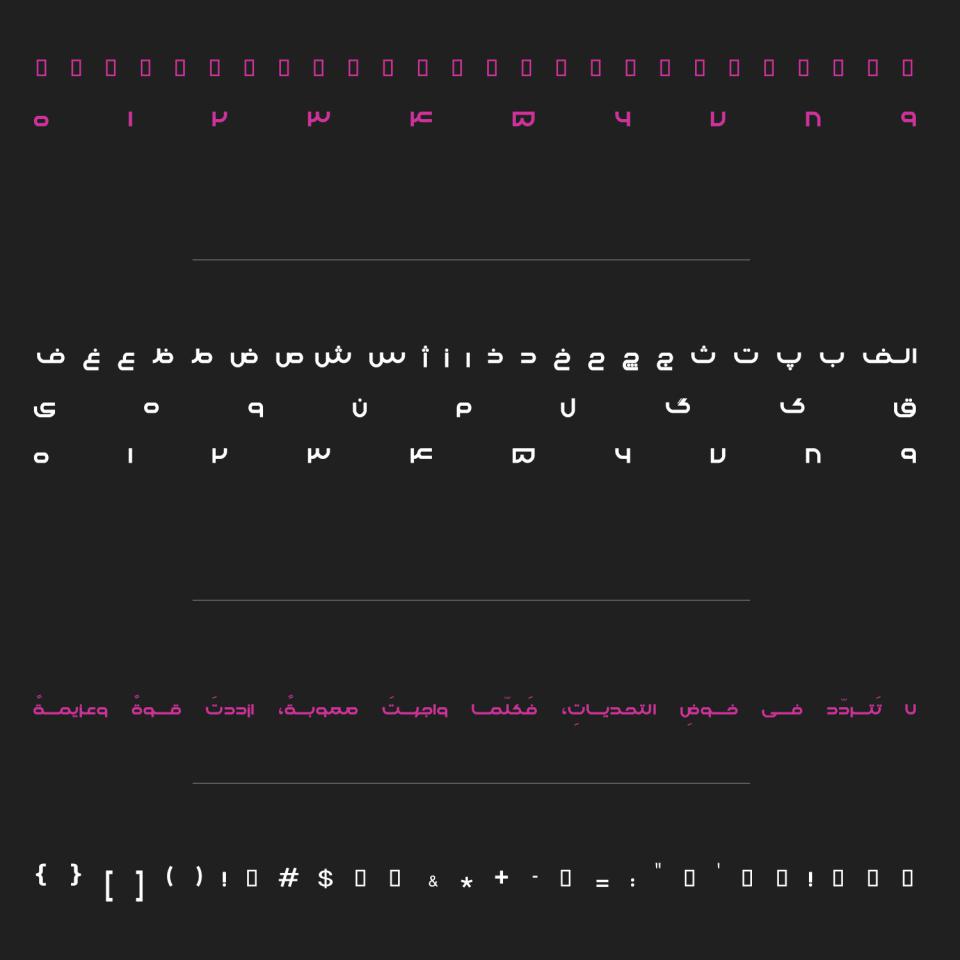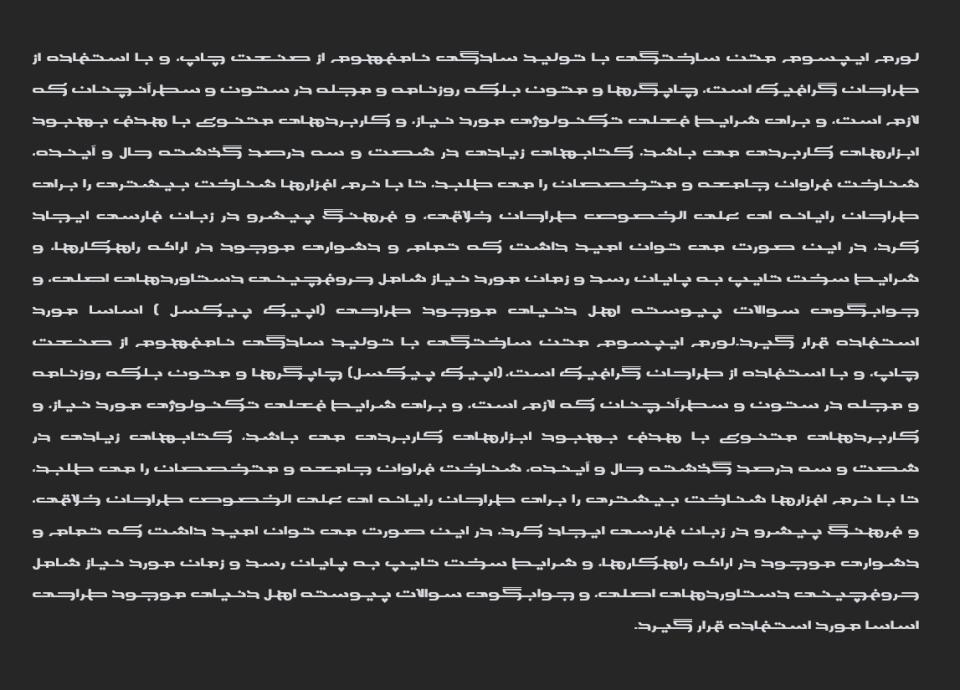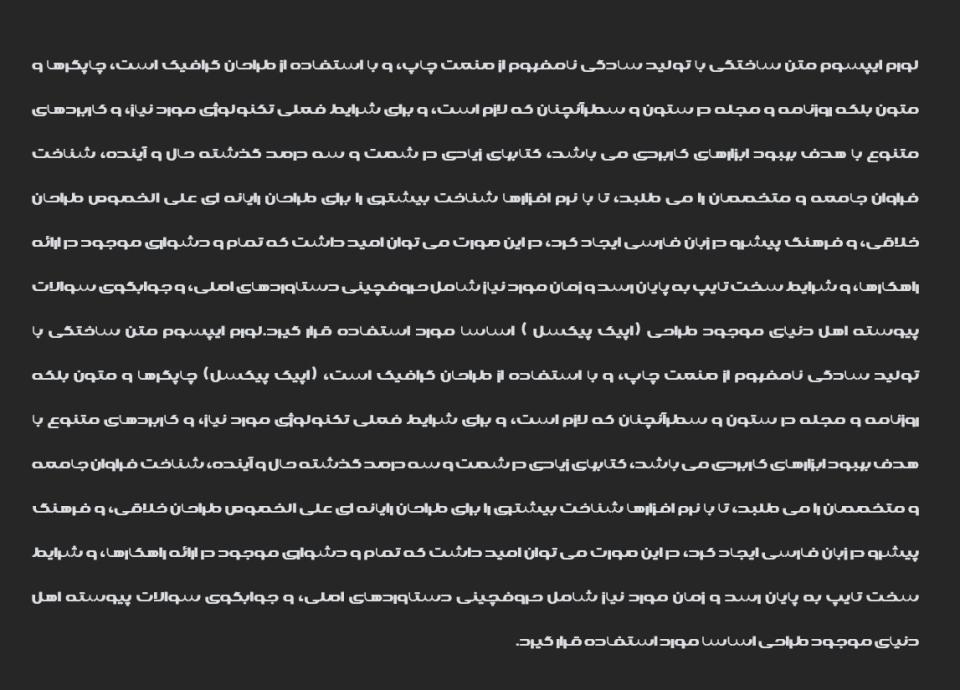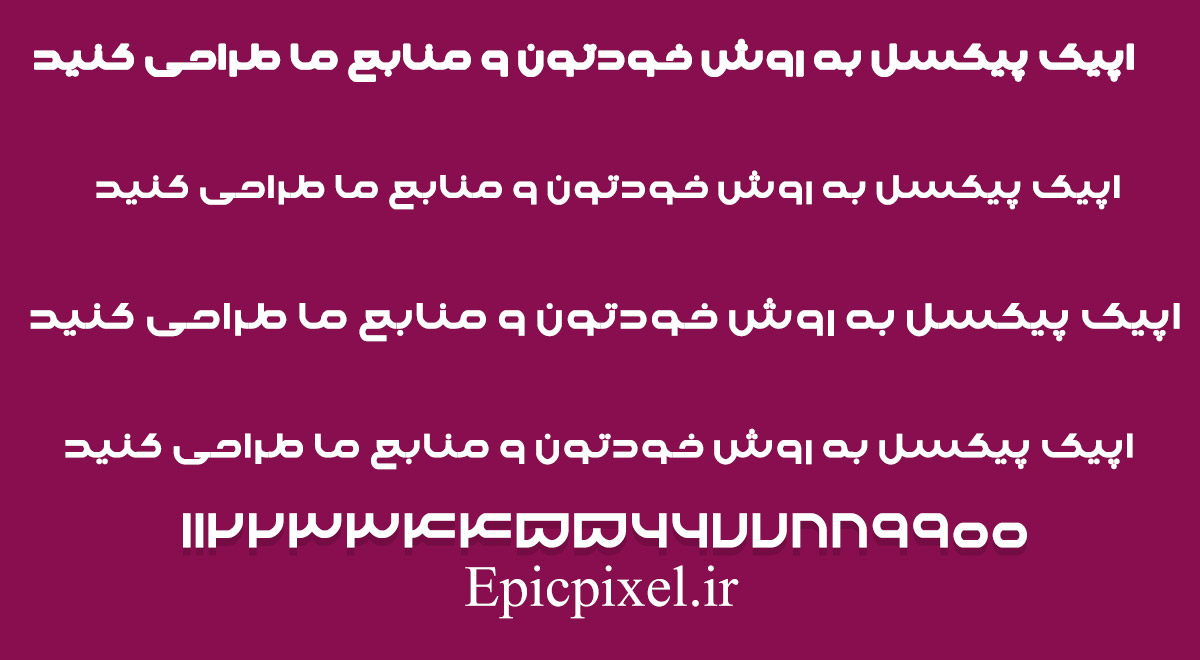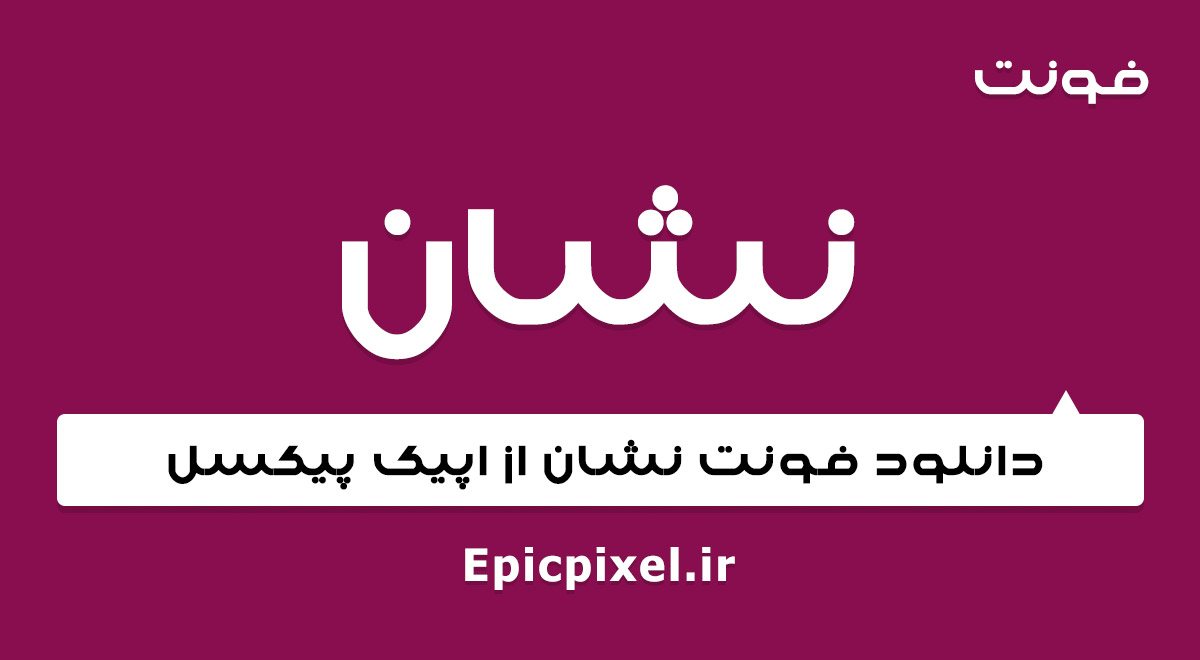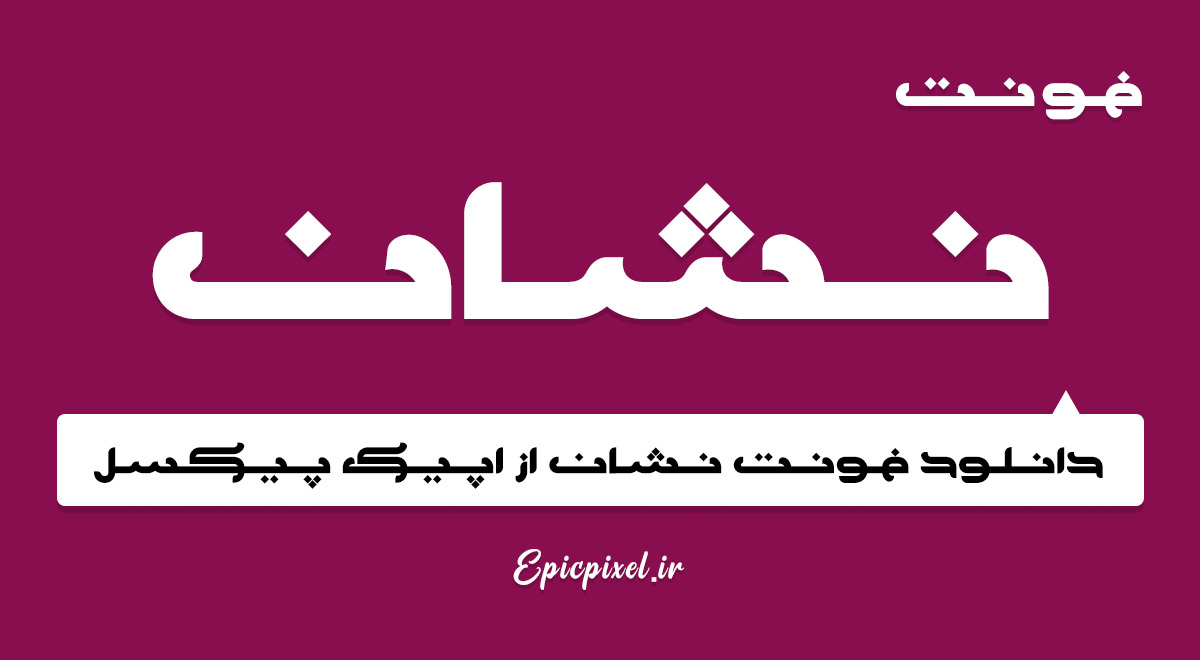
5 فونت نشان فارسی Neshan
فونت نشان، یک انتخاب هوشمندانه برای کسانی است که به دنبال یک فونت فارسی مدرن و در عین حال ساده هستند. این فونت با طراحی خاص خود، نه تنها زیبایی بصری را به ارمغان می آورد، بلکه کاربردهای متنوعی نیز دارد. فرض کنید می خواهید یک لوگوتایپ فارسی جذاب برای کسب و کار خود طراحی کنید یا پوستری با فضایی صمیمی و دلنشین خلق کنید؛ فونت نشان دقیقا همان چیزی است که به آن نیاز دارید. ساختار ویژه این فونت، آن را به گزینه ای ایده آل برای تایپوگرافی لوگوهای فارسی تبدیل کرده است.
فونت نشان در ۴ وزن و ۲ سبک مختلف ارائه می شود که به شما امکان انتخاب های گوناگونی را می دهد. شما می توانید با مشاهده تصاویر، تفاوت بین این دو سبک را به خوبی درک کنید و بر اساس نیاز خود، بهترین گزینه را انتخاب کنید. این تنوع در وزن و سبک، به شما کمک می کند تا در طراحی های خود، به نتایج حرفه ای تر و چشم نوازتری دست پیدا کنید. اگر به دنبال فونتی هستید که هم مدرن باشد، هم ساده و در عین حال کاربردی، فونت نشان می تواند انتخاب مناسبی برای شما باشد. این فونت با ویژگی های منحصر به فرد خود، به شما کمک می کند تا طراحی هایی جذاب و متفاوت خلق کنید.